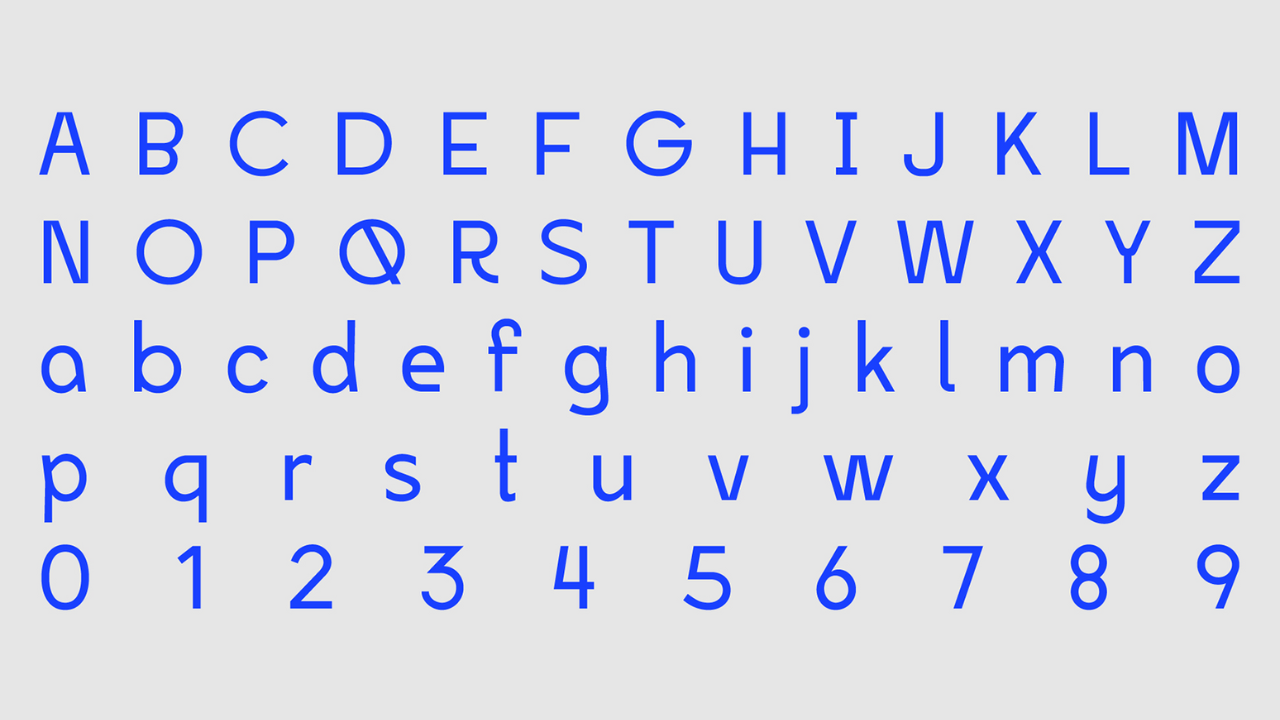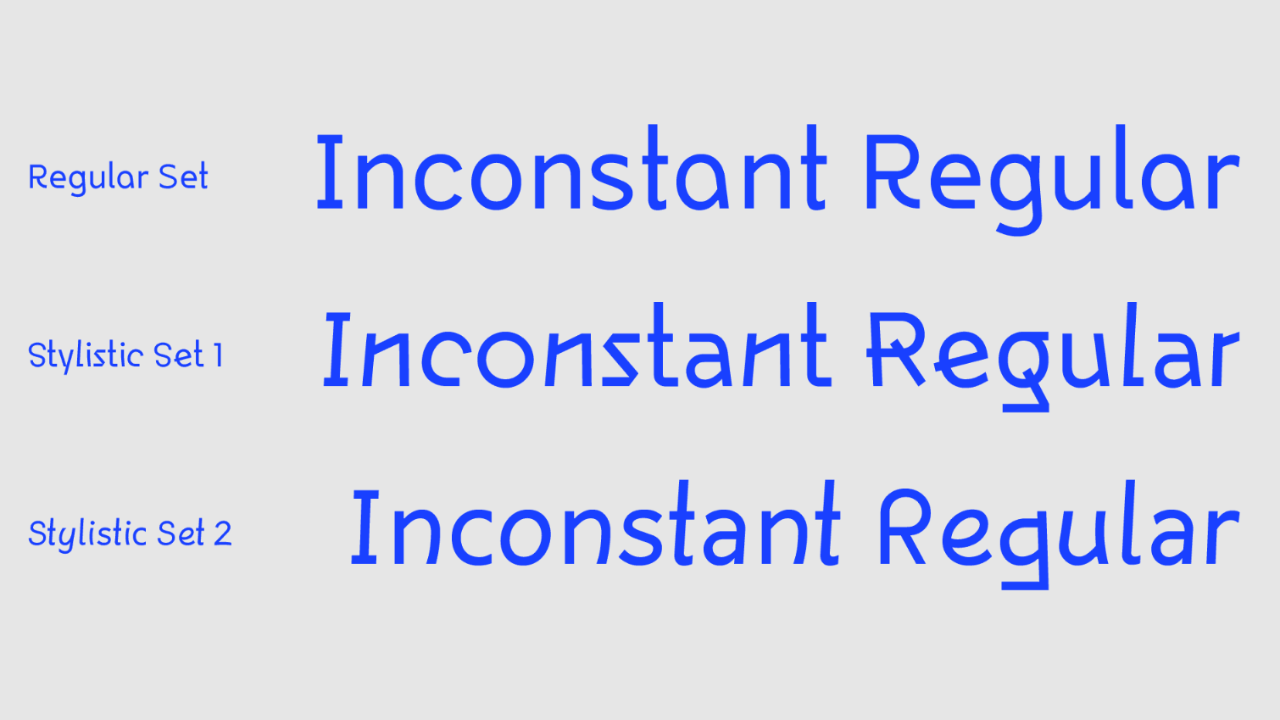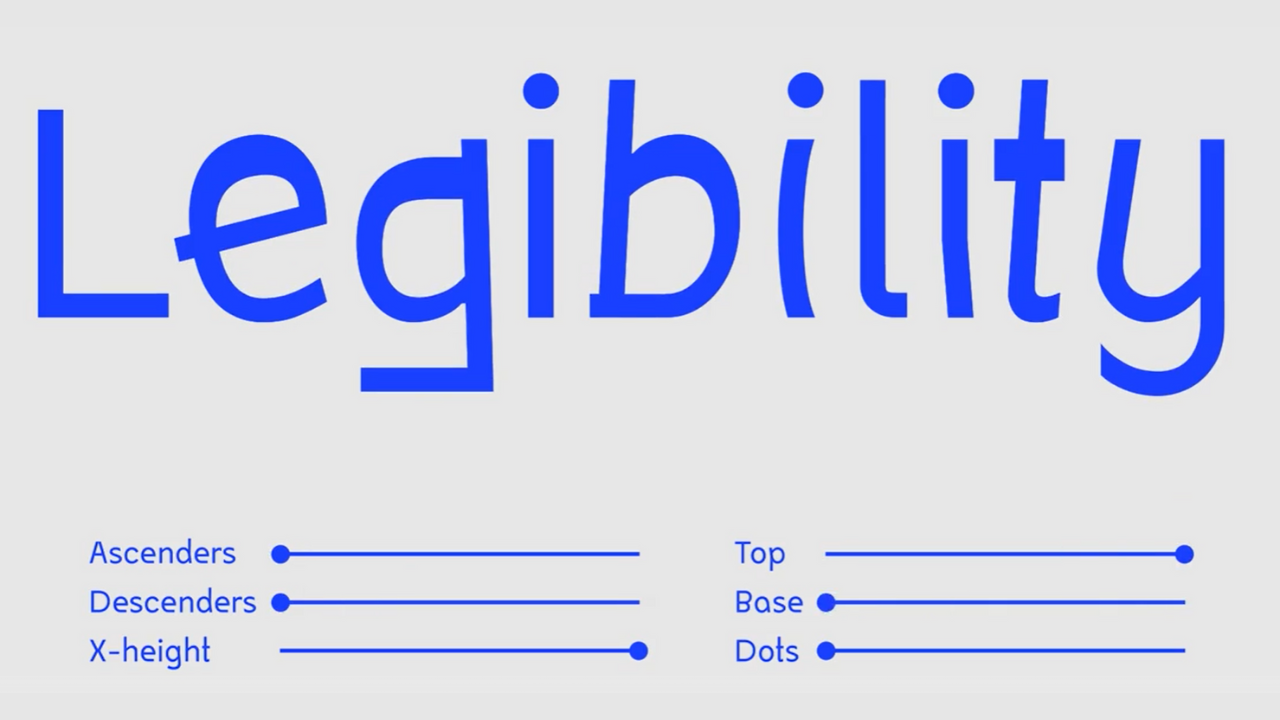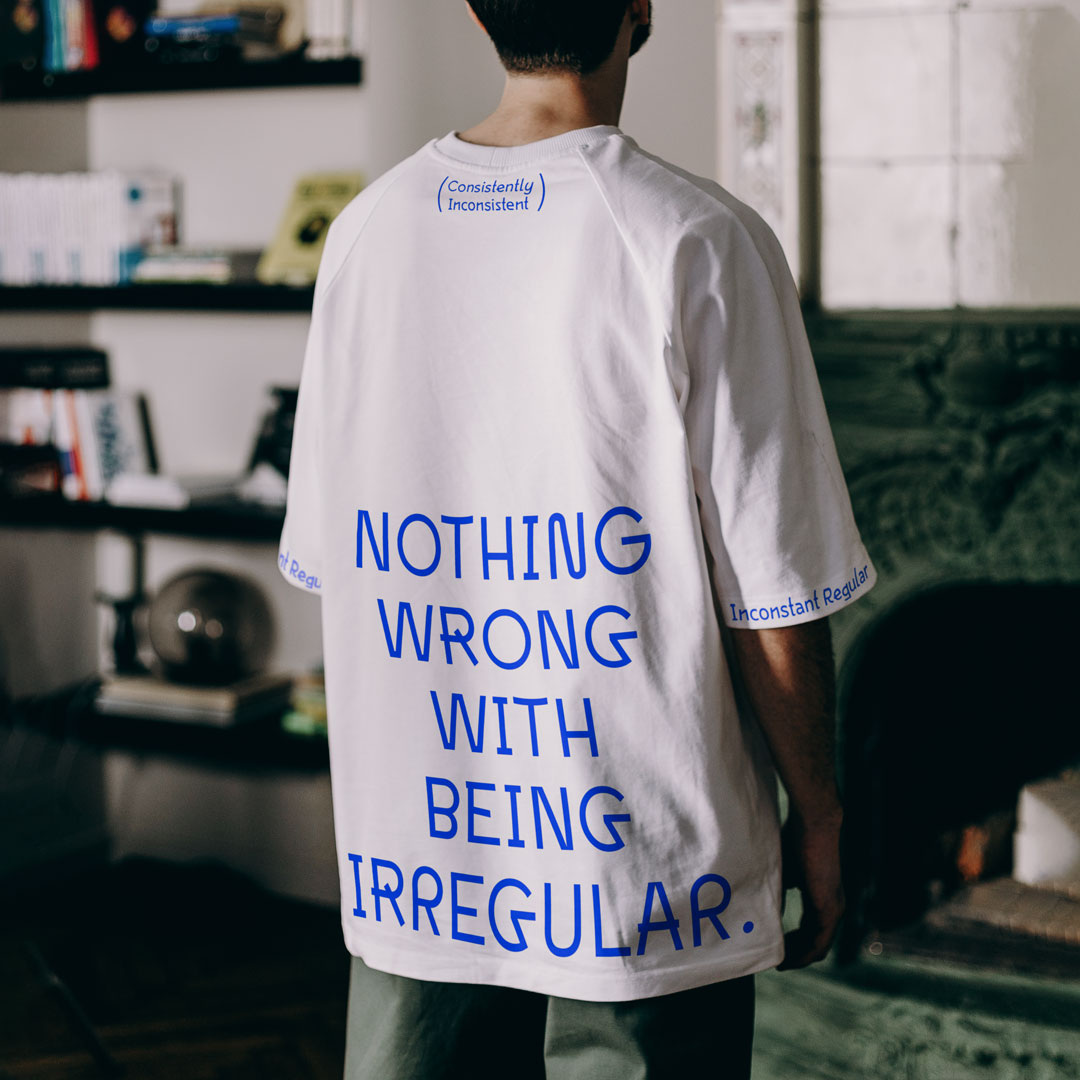
Negli ultimi anni l’accessibilità alla lettura su internet (e non solo) è diventata una vera e propria priorità per gli esperti di UI. Sulla dislessia, che colpisce oltre 780 milioni di persone in tutto il mondo, però, ci sono ancora molte ombre. Attualmente, esistono diversi font ad alta leggibilità, compreso il tanto bistrattato Comic Sans, ma la strade è lunga. Inconstant Regular nasce proprio in quest’ottica: migliorare la leggibilità per le persone con dislessia.
Fresco, attuale e inclusivo: Inconstant Regular è il carattere Sans Serif costantemente incorente e non così regolare. Come dice la descrizione, è stato creato per venire incontro sia alle persone dislessiche che ai designer. Le sue forme irregolari, le sue variabili integrate e la possibilità di combinare diversi elementi si adattano perfettamente alle esigenze personali e d’estetica.
Cos’è Inconstant Regular
Il font Inconstant Regular è stato creato in seno alla campagna “There’s Nothing Comic About Dyslexia” – Non c’è nulla di comico nella Dislessia. Si tratta di un’iniziativa in collaborazione con Dyslexia Scotland e Innocean Berlin che tratta proprio dell’inclusività di lettura. Nel titolo è presente un gioco di parole che fa capo al Comic Sans, font tanto odiato dai designer e strumento molto utile per la dislessia.
Inconstant Regular è progettato in modo tale da avere diverse alternative contestuali che consentono un’ottima convivenza tra gradevolezza grafica e leggibilità. Ben 3 diversi set di glifi possono essere usati ciclicamente per differenziare al meglio i caratteri. Tutti i set hanno dei parametri regolabili: l’interlinea tra caratteri, lo spessore del tratto, l’inclinazione e la lunghezza delle linee.
La creazione di un font ad alta leggibilità
Nella campagna “There’s Nothing Comic About Dyslexia” è stato redatto anche un documento per poter creare ex-novo un font ad alta leggibilità. I punti salienti sono 7 e prendono in considerazione tutta la struttura del font. Per prima cosa le altezze: le lettere con forme simili (“h” e “n”, per esempio) dovrebbero avere un’altezza diversa, così da essere distinguibili anche solo per quelli. Per lo stesso motivo, anche le forme e le aperture di lettere simili (“p” e “q” ad esempio) dovrebbero evitare la simmetria perfetta.
La simmetria in generale non aiuta la leggibilità: sia verticalmente che orizzontalmente le lettere non dovrebbero essere speculari. In questo modo si evita che il sopra si possa confondere con il sotto. Dare un senso di direzione, anche con l’inclinazione, rende più scorrevole il testo. Per evitare altre confusioni, è importante anche che le lettere minuscole siano completamente diverse da quelle maiuscole. Sembra scontato? Sì, ma basta pensare alla “i” maiuscola che, spesso e volentieri, si scambia per una “l” minuscola.
Un altro punto focale è il distanziamento tra le lettere: la spaziatura è fondamentale, specialmente tra le vocali, per evitare l’accavallamento dei caratteri. Anche gli inizi e le chiusure sono molto importanti: punti, virgole e segni di interpunzione vari devono essere ben distinguibili, così da aiutare a scandire la frase.
Un progetto di Brokstad Studio
Inconstant regular è una creazione del Brokstad Studio, un’associazione di designer estremamente particolare, sia nello stile che nel concetto. Sul loro eccentricissimo sito, si definiscono come uno studio di design virtuale ma anche un’iniziativa di collaborazione che va oltre i confini dello spazio fisico.
Fondato da Daniel Brokstad, lo studio è un coloratissimo non-luogo di aggregazione e di sperimentazione per artisti di tutto il mondo. Un parco giochi collaborativo in cui rompere le regole del gioco.